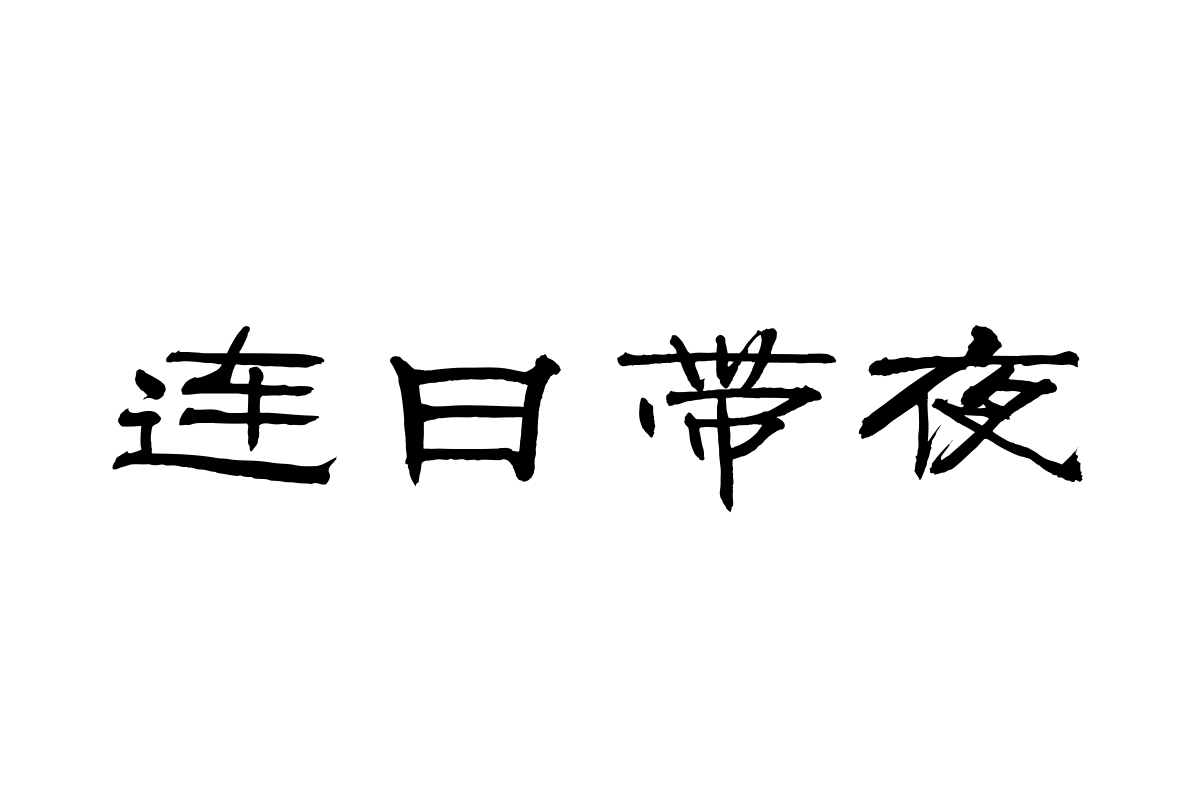
汉仪顺利松鹤体简是一款具有中国传统美感的字体,它以简洁、优雅的风格著称。这款字体的设计灵感来源于松鹤这一吉祥的象征,寓意着长寿和健康。
汉仪顺利松鹤体简的特点在于其笔画流畅、结构紧凑,给人一种轻盈而有力的感觉。它的字形呈现出一种自然的弯曲,仿佛在诉说着岁月的故事。同时,这款字体还注重细节的处理,使得整体效果更加和谐统一。
无论是用于标题、正文还是装饰性文字,汉仪顺利松鹤体简都能展现出独特的魅力。它不仅能够吸引人们的注意力,还能够传达出积极向上的精神风貌。因此,这款字体被广泛应用于各种场合,包括广告设计、书籍出版、网站界面等。